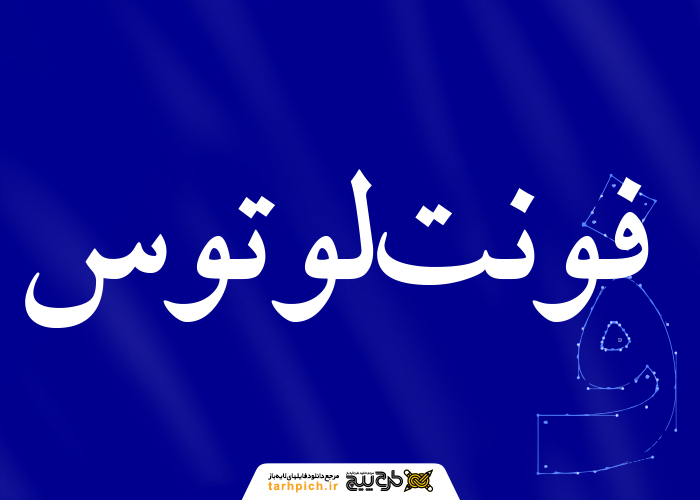
فونت لوتوس
یکی از زیبا ترین فونت های فارسی فونت لوتوس است که به دلیل طراحی هنری و انعطاف پذیری خود در بسیاری از پروژه های گرافیکی و متنی مورد استفاده قرار میگیرد.این فونت در دسته بندی فونت فارسی قرار دارد .برای دانلود فونت جدید روی لینک رنگی کلیک کنید.